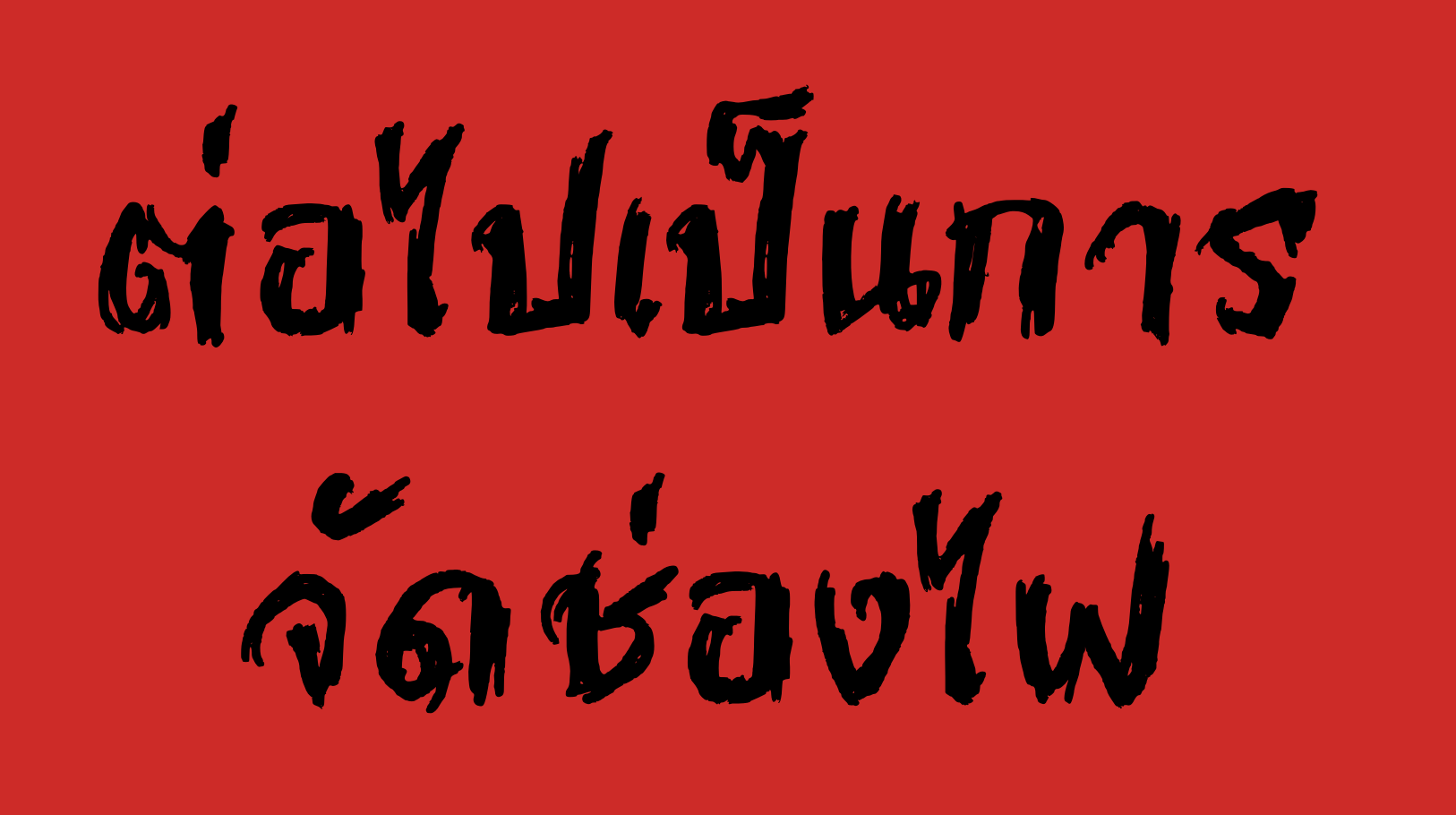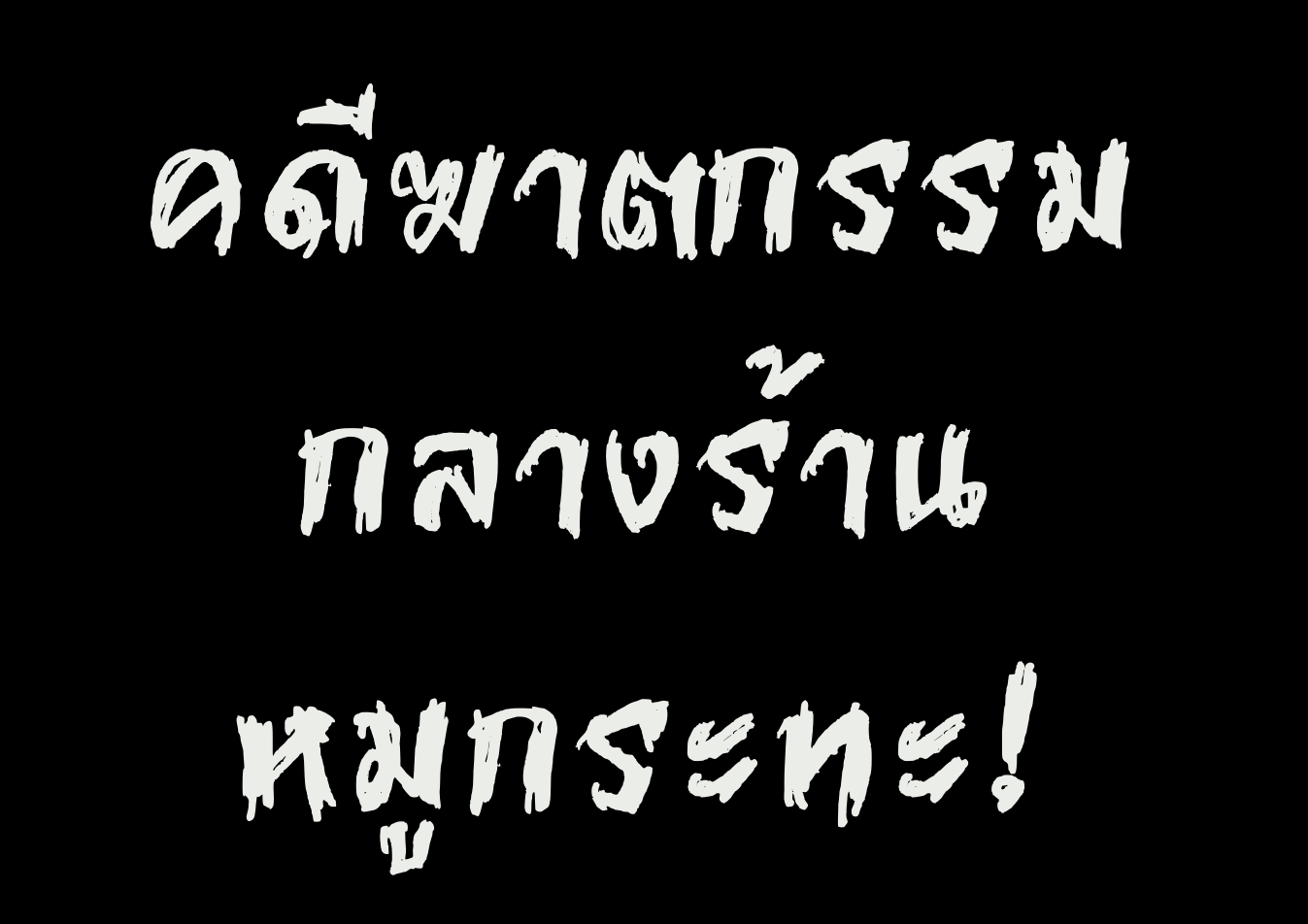
ค้างคาว (iannnnn-BAT)
นั่งรอลูกเรียน อากาศร้อนๆ เลยได้ตัวนี้มาครับ
จะทำเป็นฟอนต์แนวโหดๆ เลือดๆ แต่ก็มีกลิ่นลายมือตัวเองเช่นเคย (ที่ทำนี่ก็เพราะจะใช้เองทั้งนั้น :30:)
ตอนนี้เข้าสู่ขั้นตอนที่ 1 คือจัดแต่งตัวอักษรที่ import เข้ามาในฟอนต์แล็บ
แล้วจะทยอยอัปเดตเรื่อยๆ เมื่อว่างมานั่งทำต่อครับ
ขุดมาทำต่อครับ หลังจากดองไว้เดือนนึง :37:
ฟอนต์นี้ก็จะมาแนวโหดๆ เลือดๆ นั่นแหละ เป็น Display Font แบบที่อยากได้เอง (เช่นเคย) ครับ
ตอนนี้ทำแค่ ก-ฮ นอกนั้นยัง :30: เดี๋ยวทยอยๆ ครับ แต่อยากทำต่อเนื่องแล้วๆๆๆ
จูนขนาดเรียบร้อยครับ วันนี้สบายใจละ ค่อยๆ ทำทีละหน่อย :54:
ขุดครับ วันนี้ปล่อยฟอนต์นี้นะ หลังจากเลื่อนมานาน :3005: